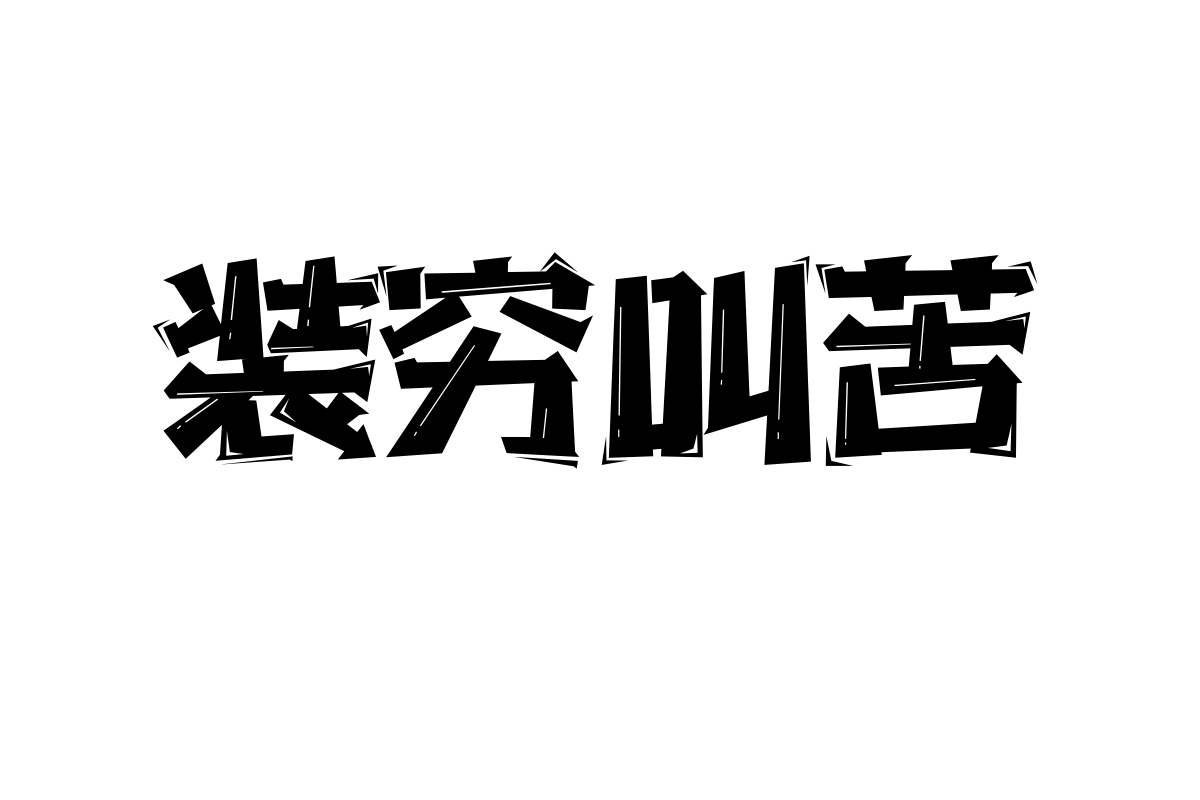
上首炫酷体是一种现代、时尚的字体,具有强烈的视觉冲击力和独特的设计感。它由多个不同的字符组合而成,每个字符都有其独特的形状和风格,使得整个字体看起来非常独特和引人注目。
上首炫酷体的笔画粗细不一,有的粗犷有力,有的纤细流畅,给人一种强烈的视觉冲击感。同时,这种字体的字形也呈现出一种动态的效果,使得整个字体看起来更加生动和有趣。
此外,上首炫酷体还采用了一些创新的设计元素,如不规则的形状、夸张的比例等,使得整个字体看起来更加独特和新颖。
总的来说,上首炫酷体是一种非常具有个性和创意的字体,适合用于需要强调视觉效果和吸引眼球的广告、标志、海报等领域。